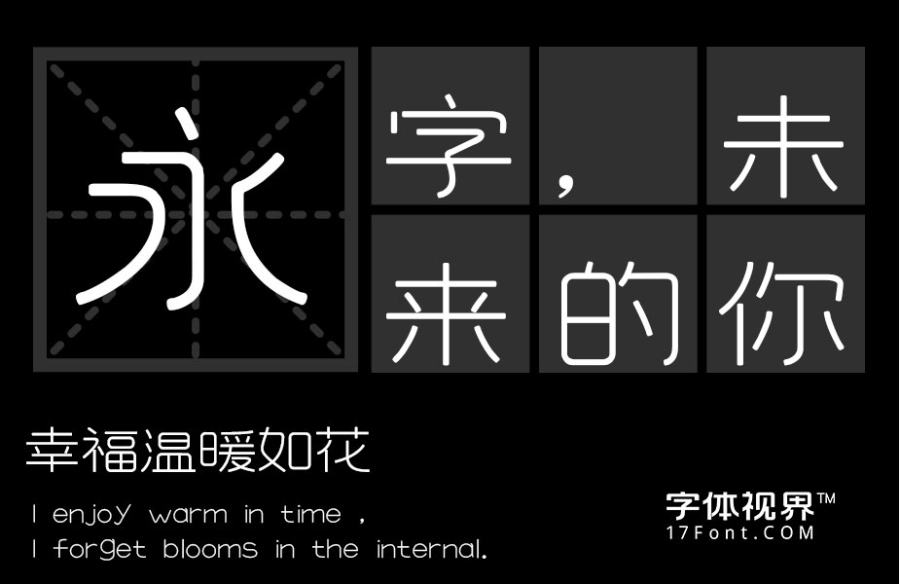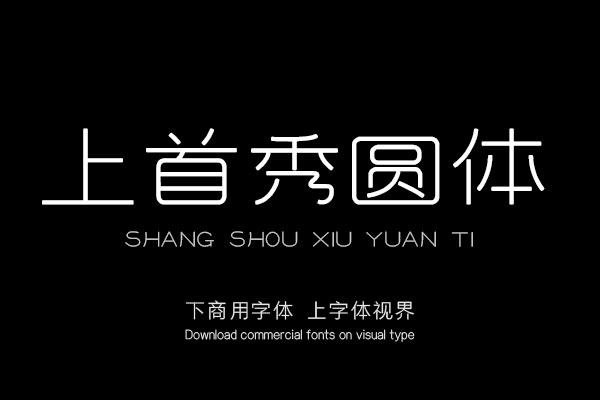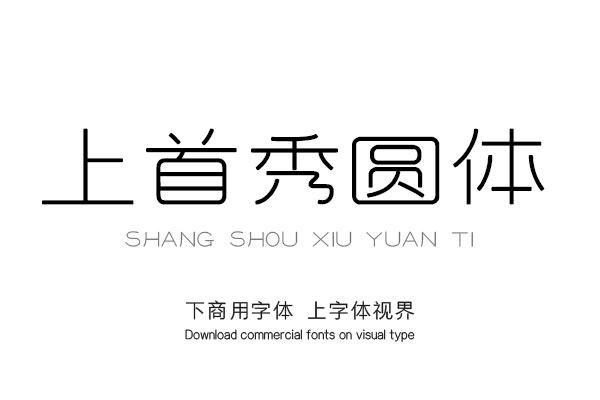
上首秀圆体,字体风清新秀丽,笔画瘦长,转角圆润,是此套字库的亮点。字库整体特征柔和、圆润,具有现代感十足,适用于搭配标志、广告标语、商业广告等高端属性。购买须知:“下载服务费”与“字体VIP”所获得字体 仅用于个人非商用, 商用请联系付费授权。本字体为电脑用字,手机没有root权限不支持直接手机换字(手机如何root,请自行百度搜索教程)。购买前请先 了解清楚后再付款 ,字体为虚拟产品无法回收 一旦购买不支持退款。